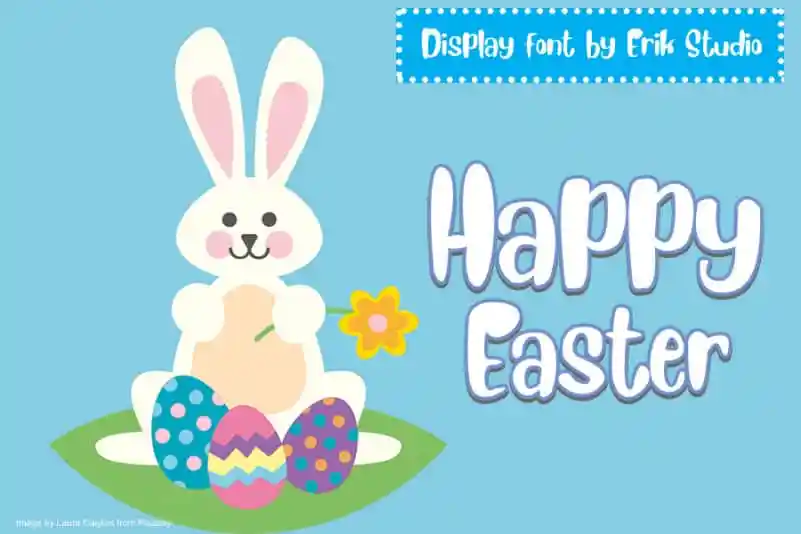
Happy Easter Display Font – Download Grátis
A fonte Happy Easter Display Font é uma graça de tipografia calligráfica que brilha ao ser escrita sobre a linha base. As letras têm um toque dançante, proporcionando um toque encantador e leve à sua obra de design. Esta font será perfeita para escrever cartas de casamento, convites ou qualquer outro trabalho que precise de uma adição romântica e pessoal. Ideal para aqueles desejosos de dar vida a suas criações com um toque amigável e delicado, Happy Easter Display Font é uma escolha perfeita para quem procura uma fonte que se destaca no design gráfico brasileiro, caracterizada pela simplicidade e beleza da cultura do nosso país.